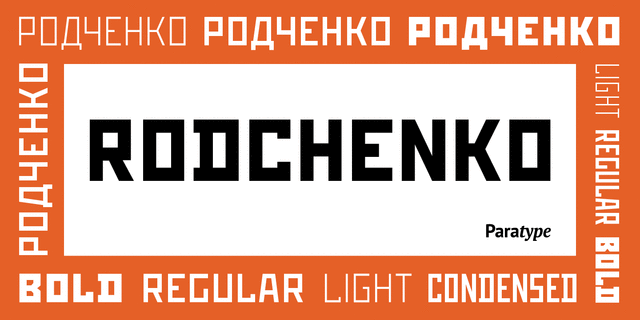
Гарнитура разработана в фирме ParaType в 1996-2002 году (дизайнер Тагир Сафаев) на основе шрифтовых работ русских конструктивистов 1920-30-х годов Александра Родченко, Варвары Степановой, Владимира и Георгия Стенбергов, Густава Клуциса и других художников. Геометрически сконструированный гротеск, имеющий только прописные знаки и капитель, образованные прямыми линиями. Предельно упрощенный, этот шрифт воспринимается как символ русского авангарда. Применяется в рекламе и акциденции.
серьезный, убедительный, твердый, железный, надежный, мужественный, уверенный, стальной, ностальгический, тоталитарный, стабильный, громкий, ровный, сильный, кондовый, устойчивый, политический, коммунистический, революционный, смелый, простой, пролетарский, точный, прямоугольный, индустриальный, техногенный, военный, армейский, солдатский, урбанистический, грубый, рабочий, мотивирующий, железнодорожный, амбициозный, городской, инженерный, статичный, автоматический, чертежный, брутальный, игровой
война, армия, оружие, машиностроение, флаг, митинг, политика, шахта, завод, металлургия, станок, инструмент, строительство, стройматериалы, тара, склад, порт, ящик, патроны, архитектура, конструктор, чертеж, техника, промышленность, электростанция, энергетика, ремонт, урбанистика, депо, шахтер, каска, униформа, вагон, авиация, самолет, страйкбол, стройка, обувь, коворкинг, железная дорога, город, инженер, автоматика, прибор, рабочий, забастовка, протест, кубики, лего Стилистика:
Добролет, Моссельпром, Резинотрест, Росгосстрах, Пионерские семечки, Ленгиз, Провідна